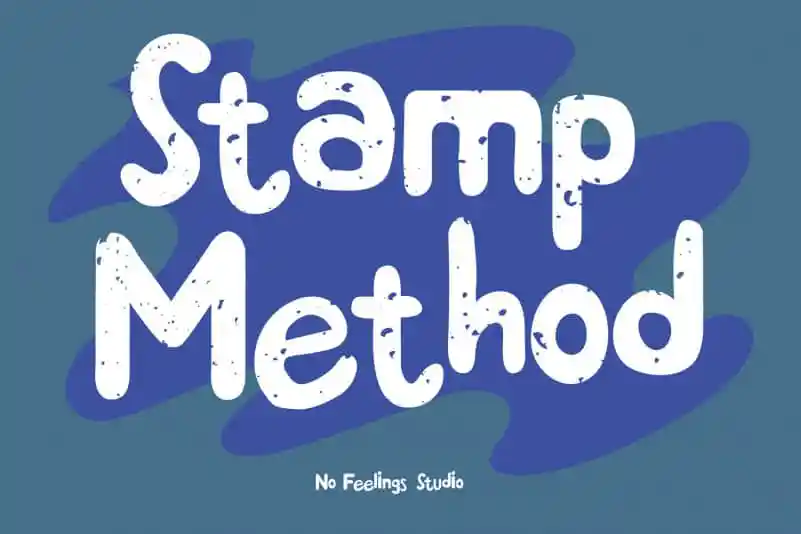
Stamp Method Display Font – Download Grátis
A Stamp Method Display Font é uma criação que nos transporta para um mundo onde a tipografia vintage se encontra com as tendências contemporâneas. Inspirada nas famosas tipografias dos anos 90, essa fonte mantém seus traços robustos e moderno graças à influência de estilos artísticos atuais. Com uma liberdade na forma que destaca sua simplicidade elegante, ela se destina a complementar qualquer projeto e fazê-lo destacar-se ainda mais. Esta font é um presente para designers com sensibilidade nostálgica, aqueles que apreciam o charme arcaico combinado com os novos horizontes da arte. Seja em cartazes de mídia social ou em gráficos publicitários, Stamp Method Display Font oferece a perfeita combinação entre uma história contada através das linhas e um futuro brilhante visualmente. Com sua proposta única, não é difícil perceber que essa font não se encaixa ao acaso. É um ato de criatividade que busca estabelecer um diálogo entre o passado e o presente. Convidamos você a explorar este universo gráfico único, onde a Stamp Method Display Font pode fazer qualquer projeto sua, sem parecer forçado ou fora do lugar.